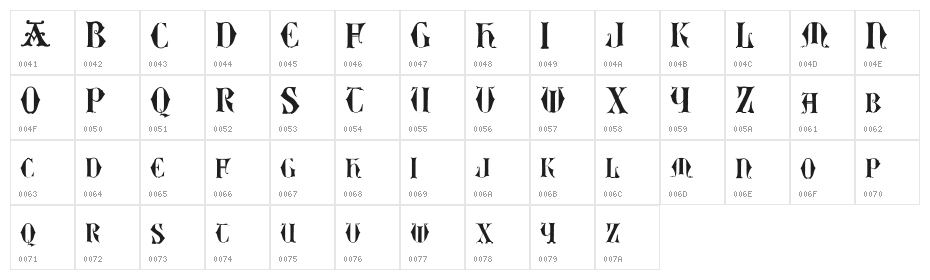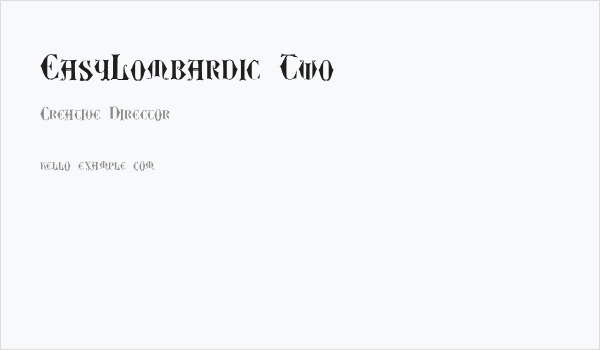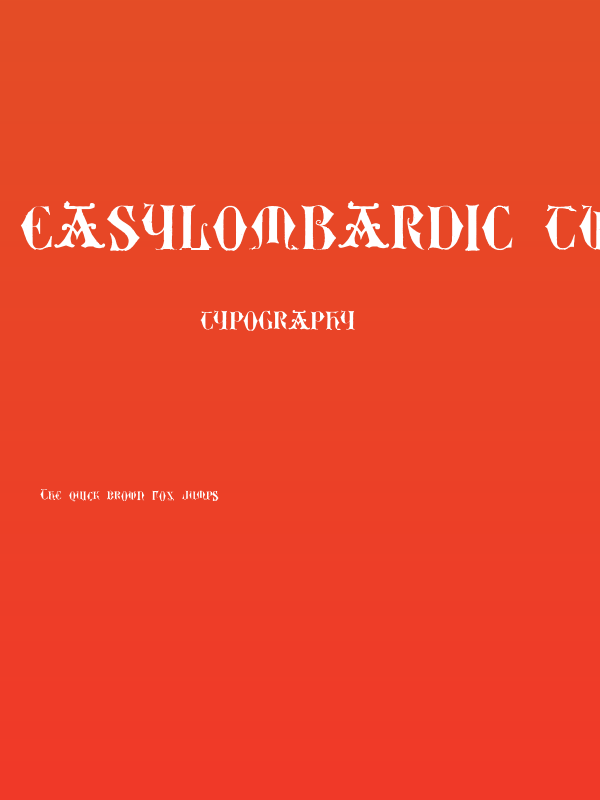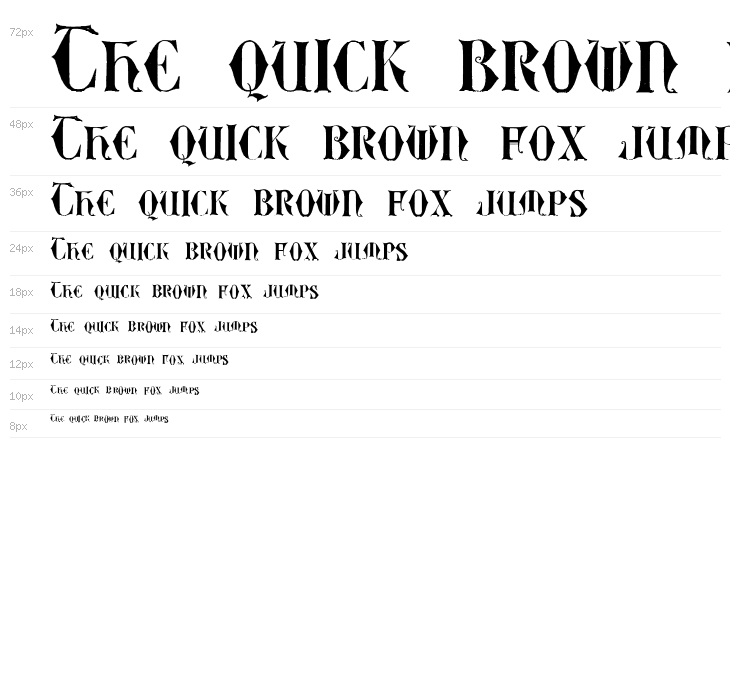
EasyLombardic Two Font
| Kategorien | Gothic |
| Gesamtstil | Vintage |
| Anwendungsfall | Headlines, Logos, Decorative text |
| Vorgeschlagene Projekte | Ideal for historical documents, fantasy-themed designs, book covers, and decorative invitations. |